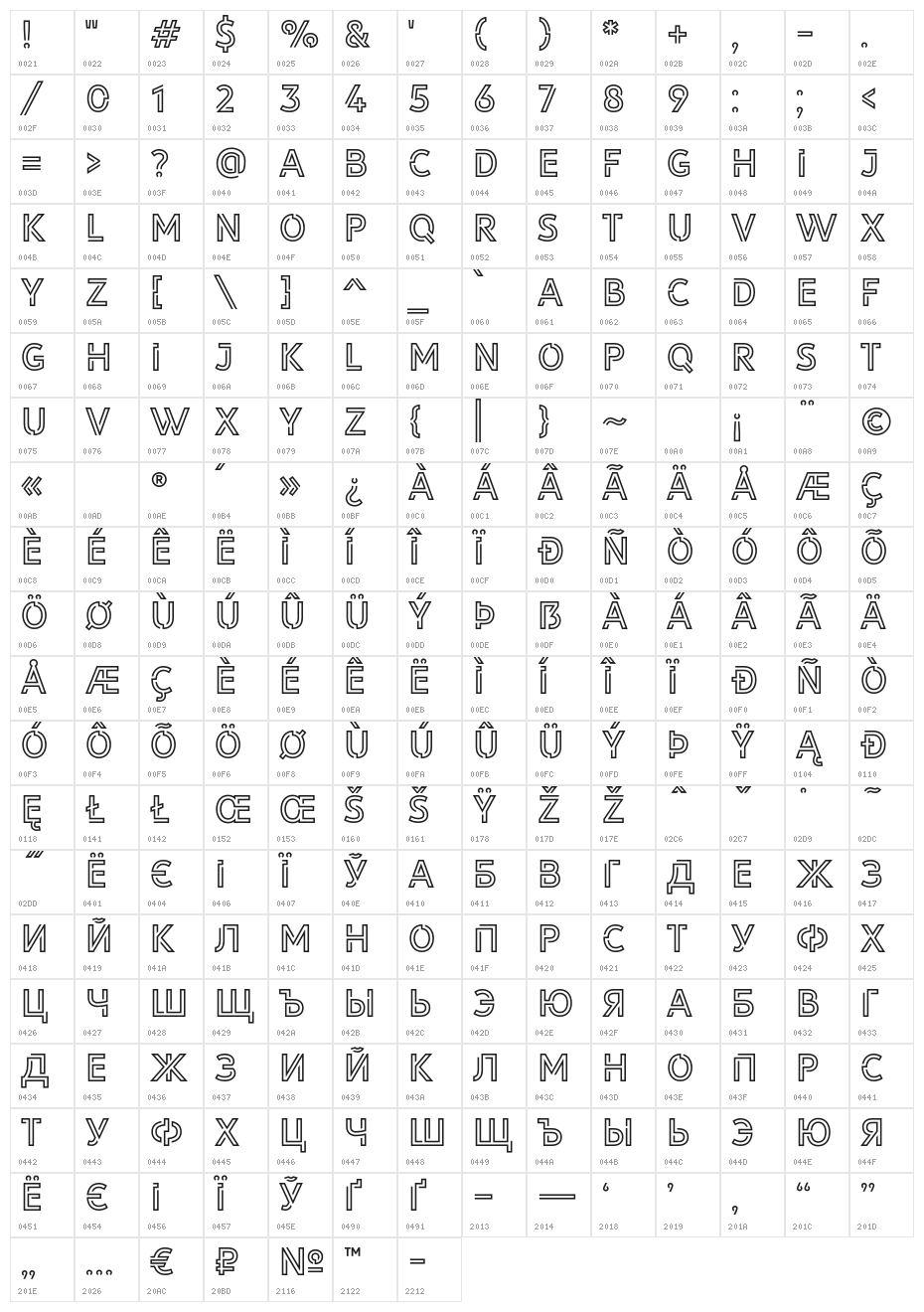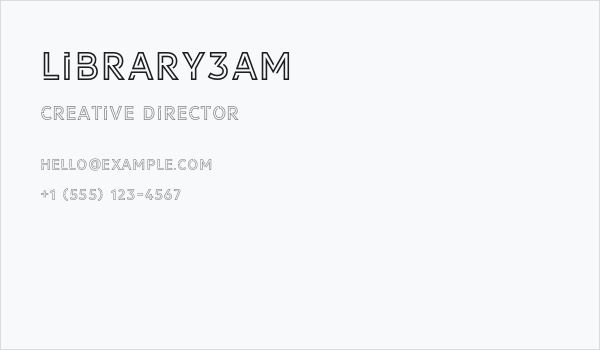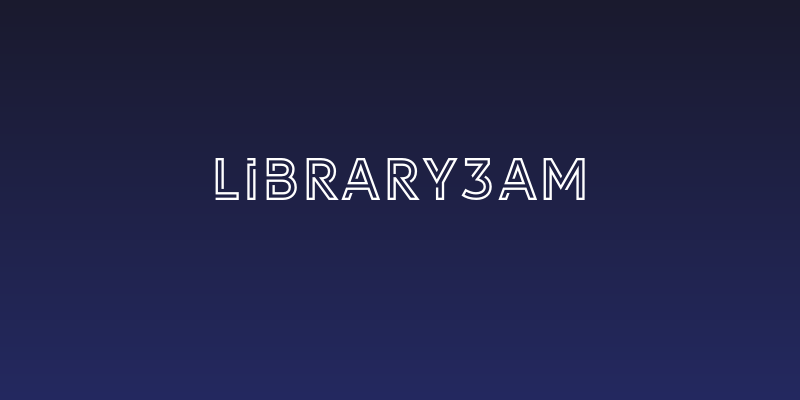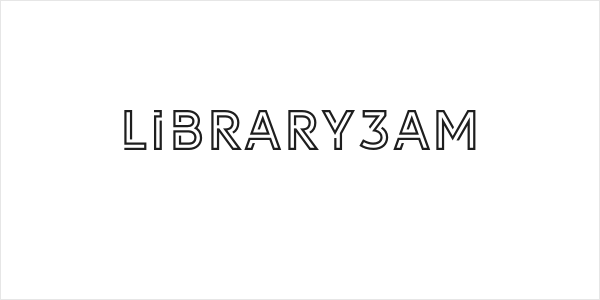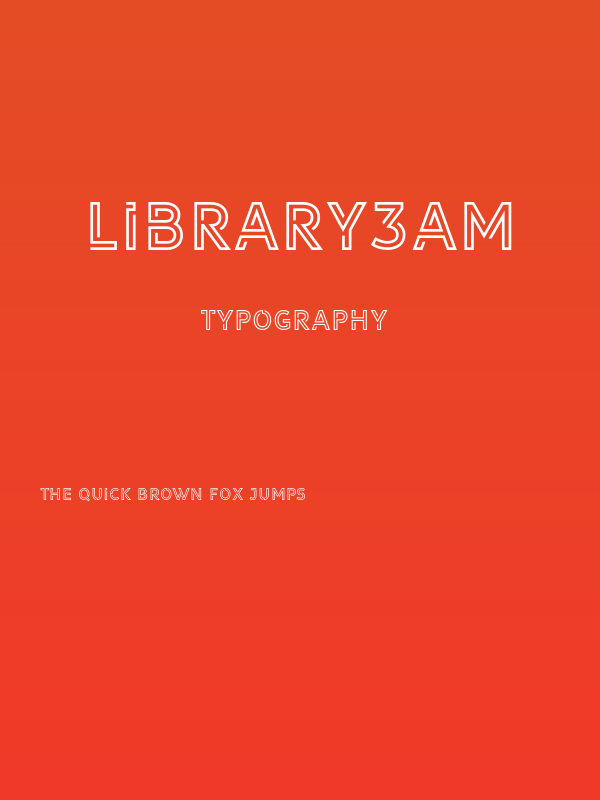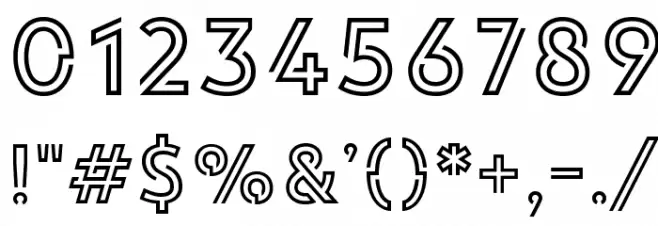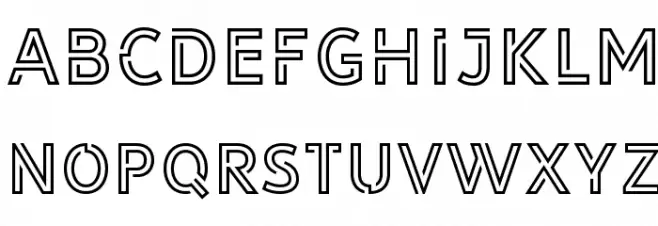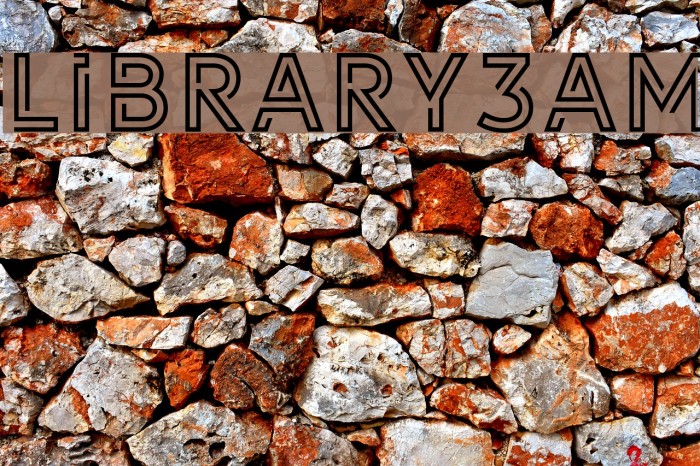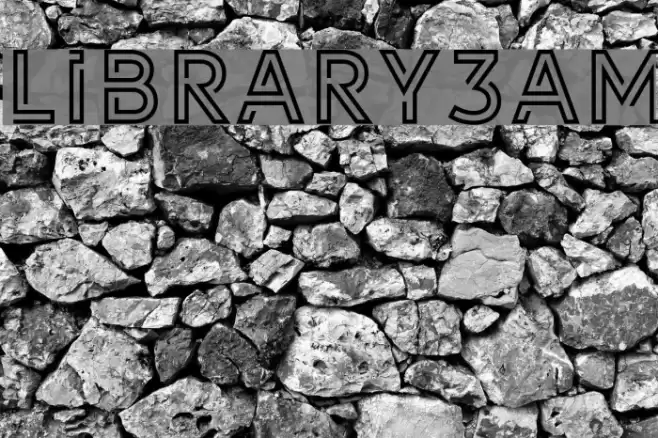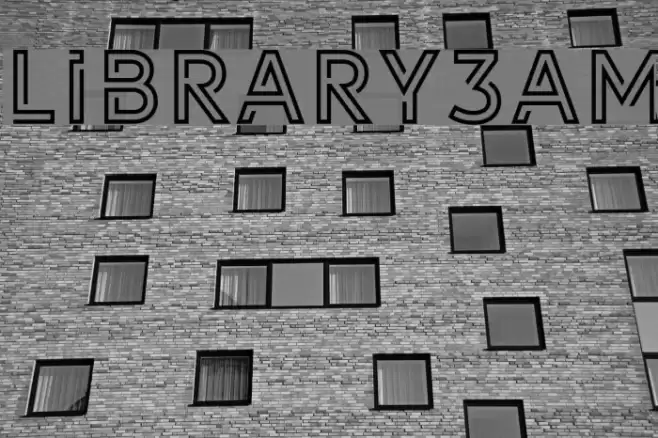
LIBRARY3AM Font
✎ Outline
| Projetos propostos | Ideal for branding, headlines, posters, and digital media where a modern and impactful style is desired. |